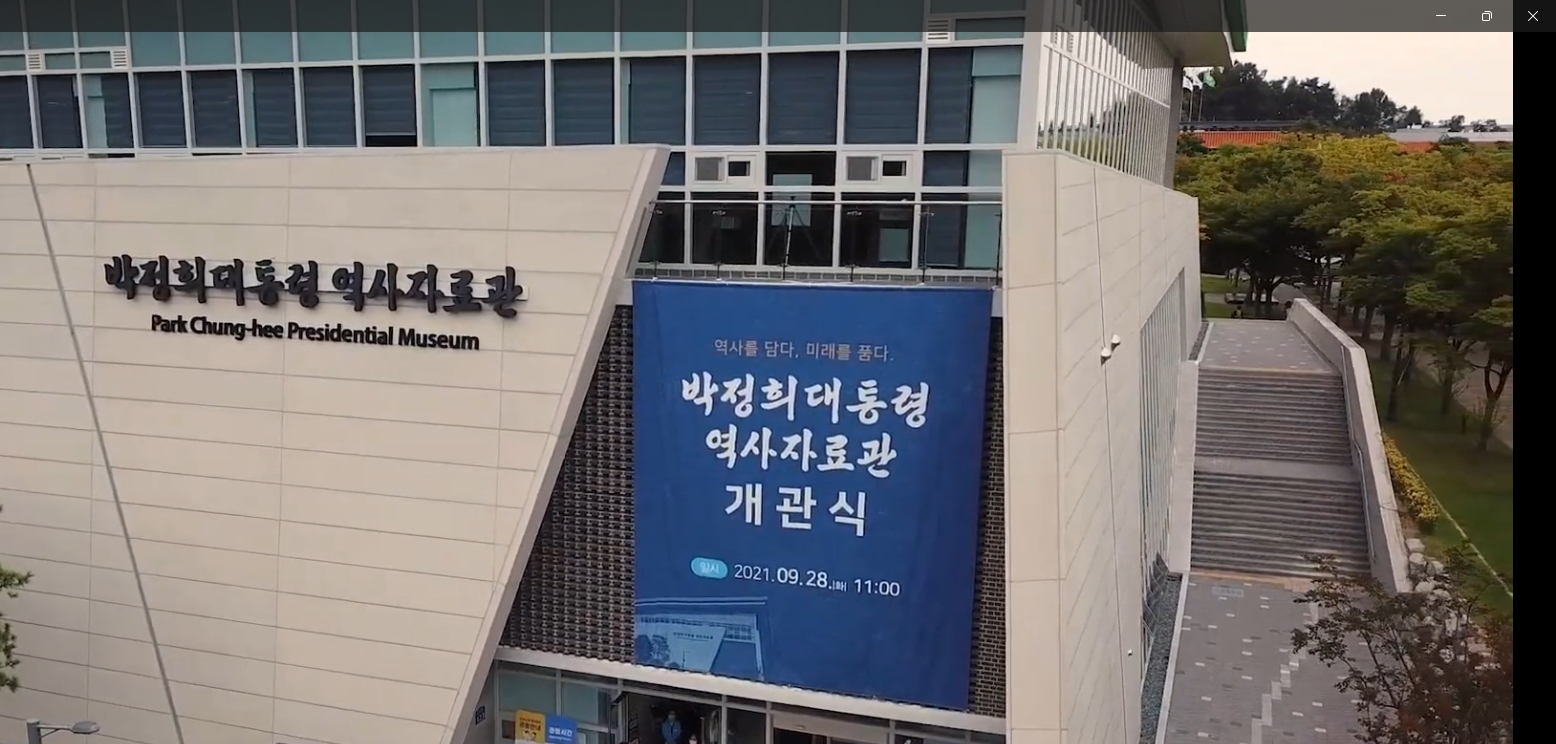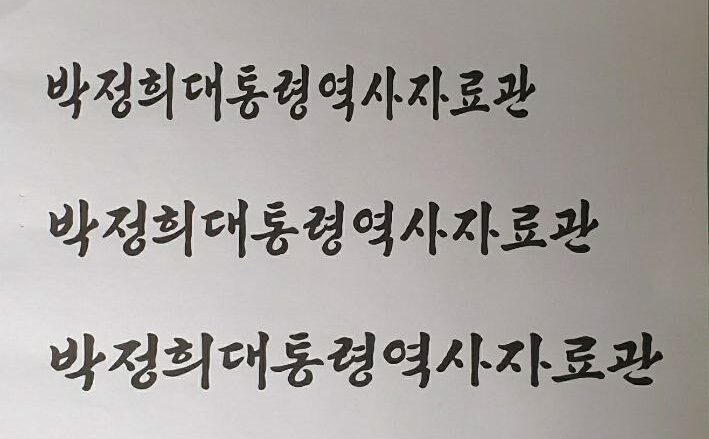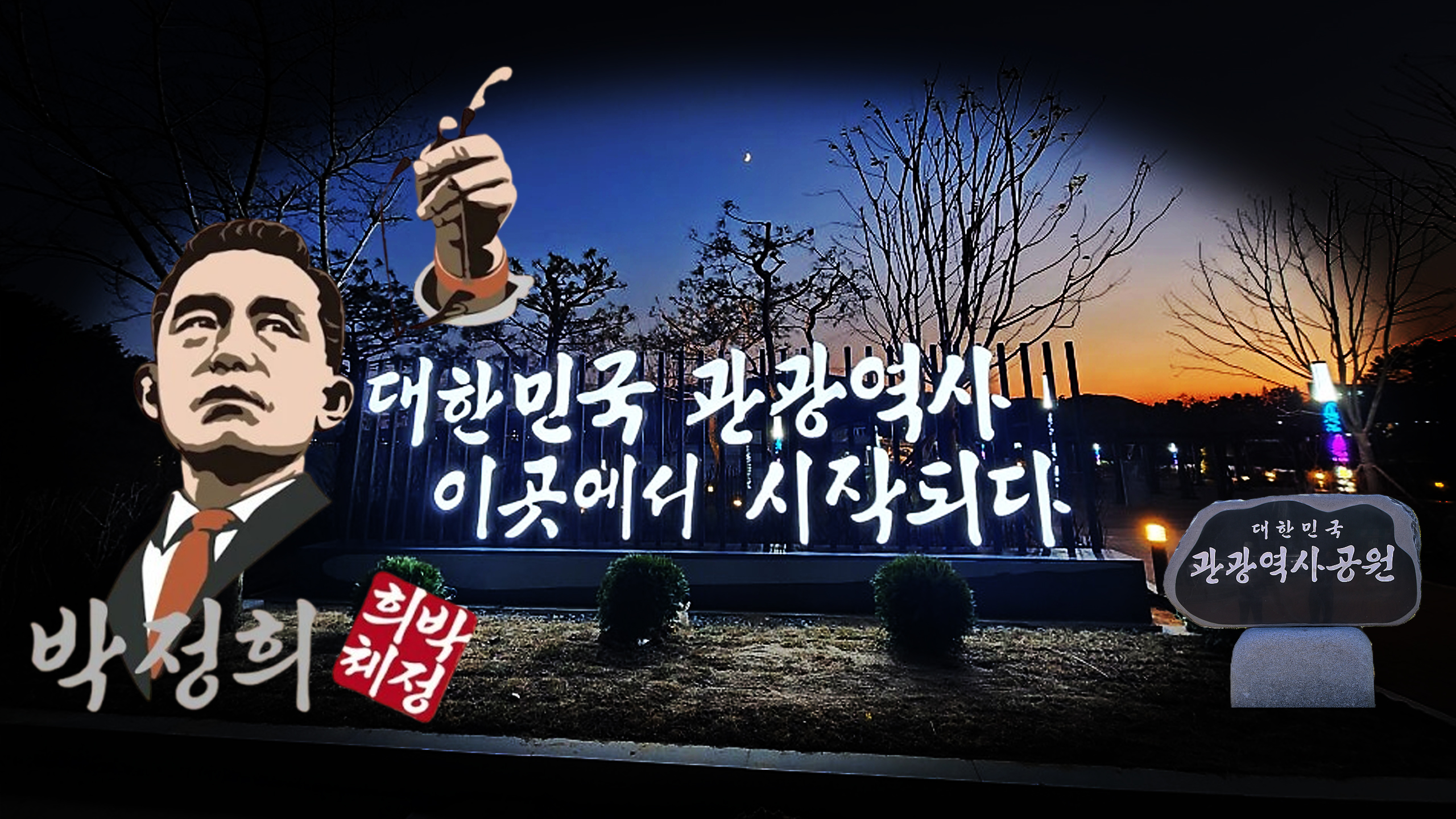
《박정희서체》
대한민국 역사를 서체로 세기다
조국근대화의 숨결, 《박정희서체》갤러리
“구미 생가. 『박정희대통령역사자료관』정면과 측면에 배치된 묵직한 필체는 《박정희서체》개발자인 필자가 직접 디자인한 것입니다.”
《박정희국력체》_L
《박정희국력체》_M
《박정희국력체》_W
[ 세 종류의 글씨체 디자인 ]
경주,《박정희서체》로 역사를 세우다
” 『대한민국 관광역사공원』입구, 『대한민국 관광역사 여기에서 시작되다』와 기념석 『대한민국 관광역사공원』의 필체는
박정희 대통령 생전 친필 휘호를 바탕으로 현대적 미백을 디자인 한 작가의 《박정희서체》로 제작되었습니다.”
※밤하늘과 호수를 밝히는 야간 조명
이 조형물도 직접 개발한 《박정희서체》로 제작하였습니다.